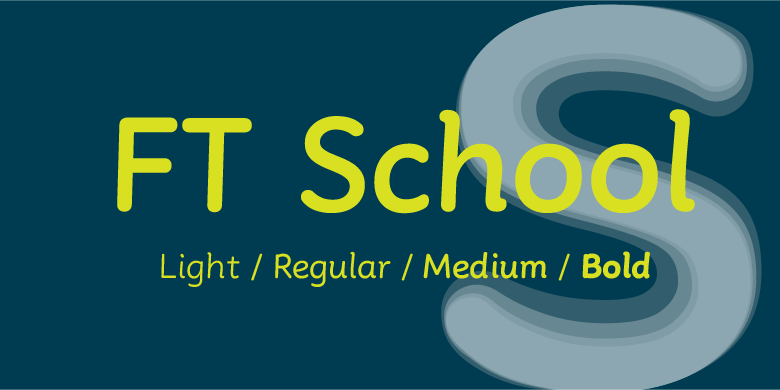
FT School
无衬线体
FT School的造型设计灵感来源于中国衡水中学特别为英语高考应试而设计的一种书写字形。该字以其工整、易读、易认的特点而广受好评。每个字母都规规矩矩,没有鲜明的特性和个性,确保视觉上的清晰度和辨识度,既符合考试对卷面整洁美观的要求,又有助于阅卷老师快速准确地捕捉答题信息,避免因字迹不清导致的误判或失分。
凭借其独到的优势,这种书写字体在教育领域迅速赢得了广泛的认可,被众多教育从业者、教育培训机构以及学校系统采纳并推荐。它成为学生们备考时练习书写的首选,也是提升考试成绩、增强卷面竞争力的有效工具。FT School借鉴并融入了这一字体风格,旨在为教育行业出版提供一个更加方便的工具来进行应试教学。